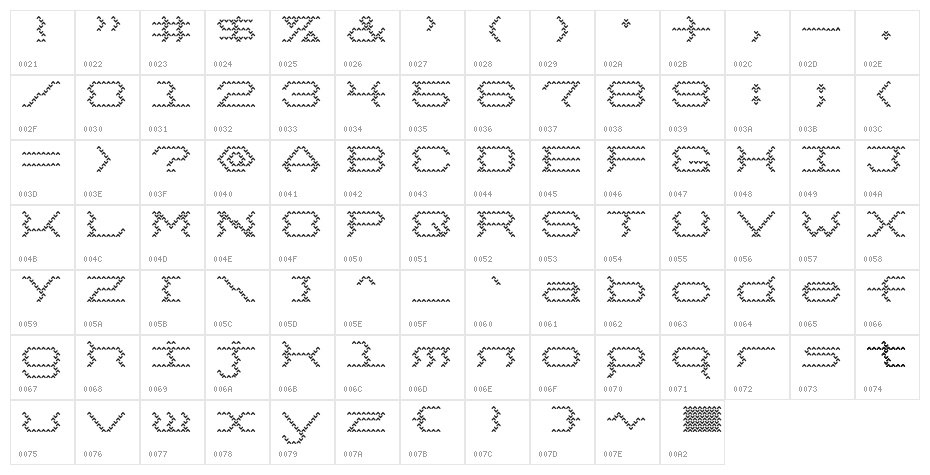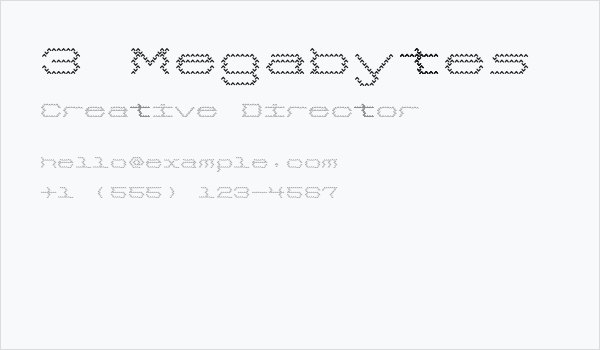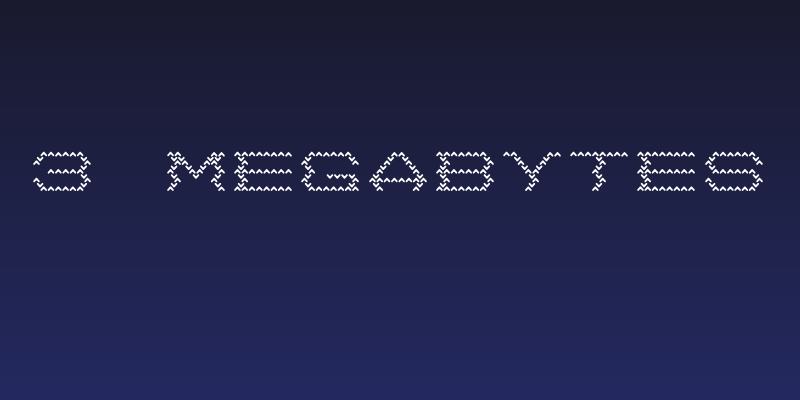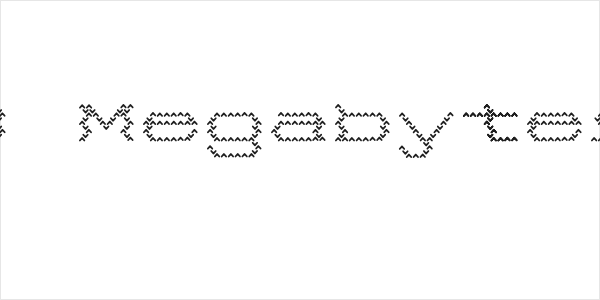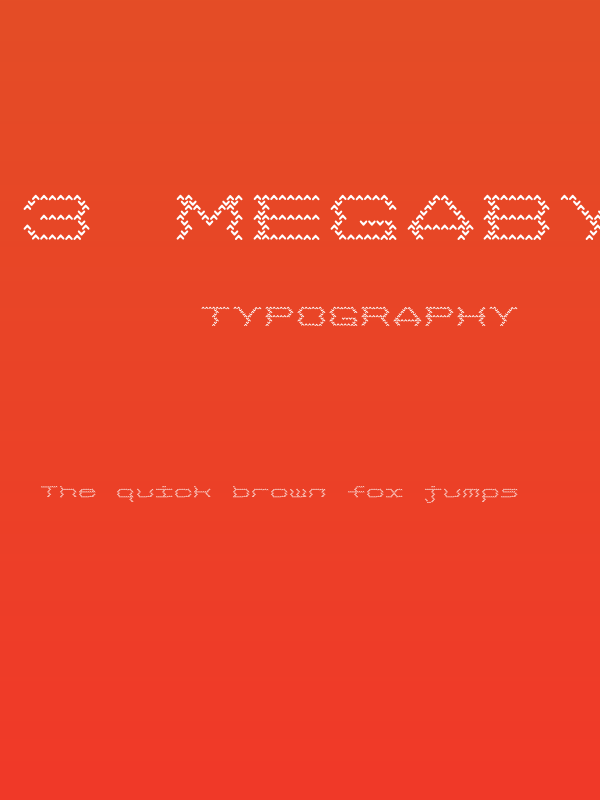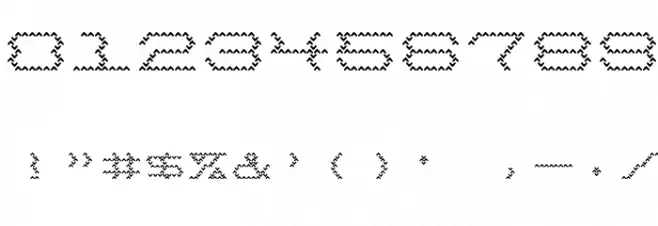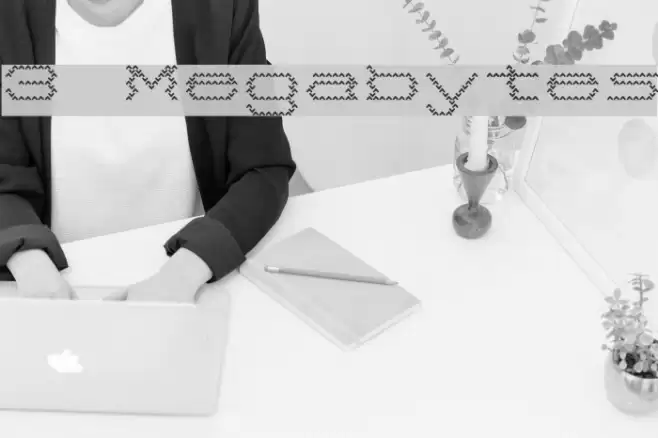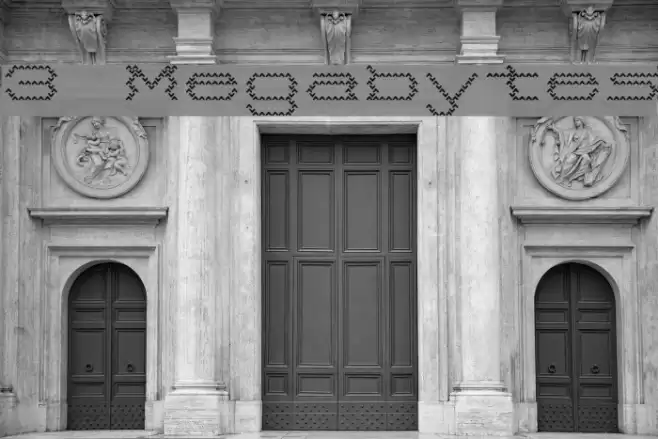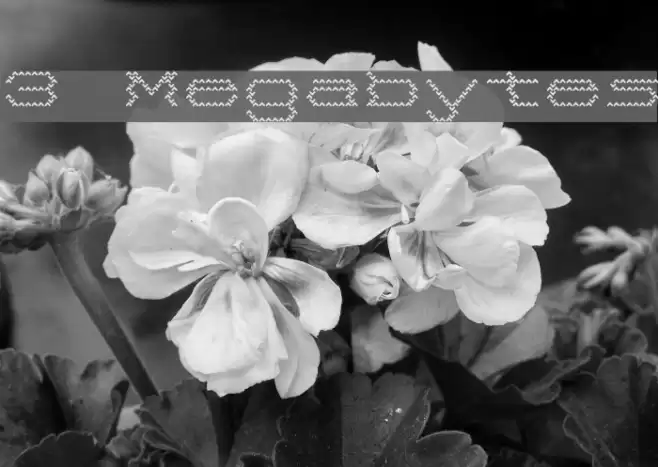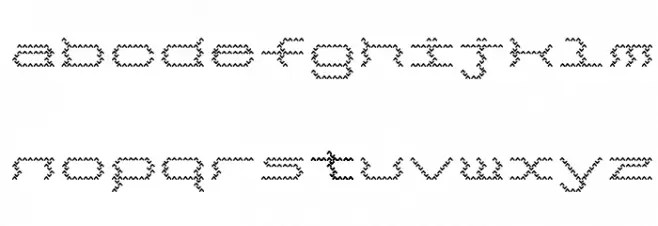
3 Megabytes Font
✎ Dotted
| Categorie | Dotted |
| Caso d'uso | Logos, Posters, Creative Titles |
| Progetti proposti | Ideal for craft-themed projects, playful branding, children's books, or any design requiring a textured, handmade feel. |